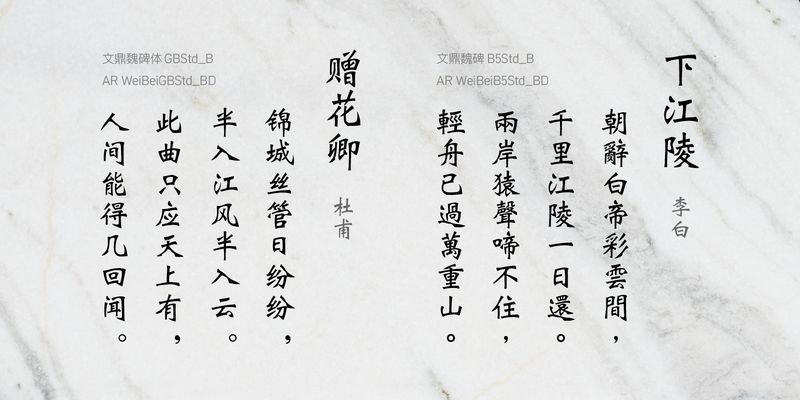
AR WeiBeiB5 no solo aúna dureza y suavidad, sino que también recuerda a las inscripciones en piedra, lo que da como resultado una tipografía suave pero firme. La moderna Weibei ha evolucionado de la tradicional que se originó en las inscripciones en piedra chinas de las dinastías del norte.